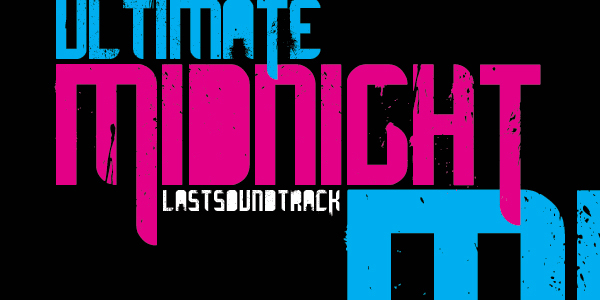
ultimate MIDNIGHT
Ultimate Midnight od Last Soundtrack to darmowy, wyrazisty krój pisma typu display, utrzymany w stylistyce nocnych plakatów. Litery są szerokie i mocne, a ich faktura – dzięki drobnym kropkom i poszarpanym krawędziom – sprawia, że font wygląda na zużyty, jakby pochodził z druku, i ma w sobie sporo surowej energii.
Świetnie pasuje do ulotek muzycznych, nagłówków w stylu horroru, plakatów klubowych, grafik streetwearowych czy tytułów, gdzie słowa muszą mieć mocne uderzenie. Jako darmowy font, doskonale sprawdzi się też w logotypach, monogramach i krótkich nagłówkach, ponieważ kapitałki zachowują solidną, blokową formę, nawet gdy tekstura łamie ich powierzchnię.